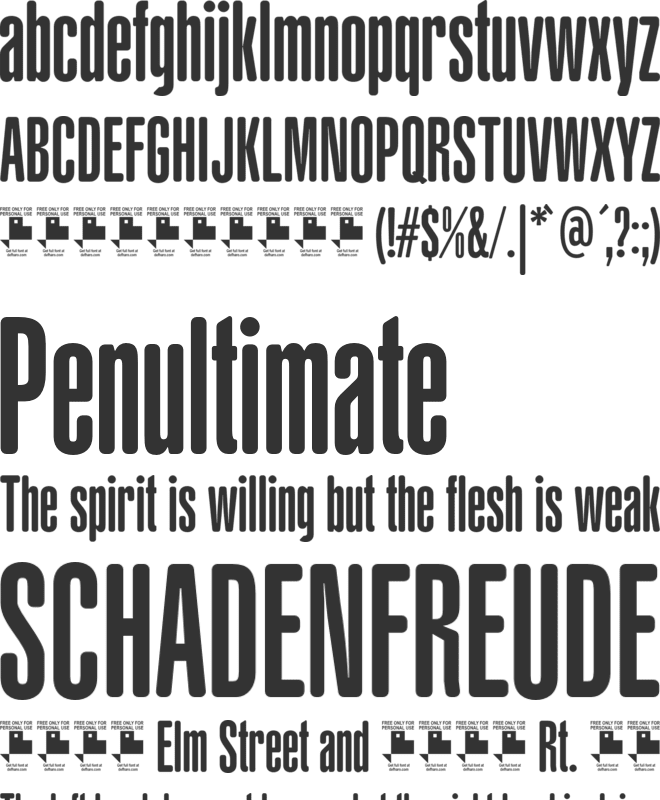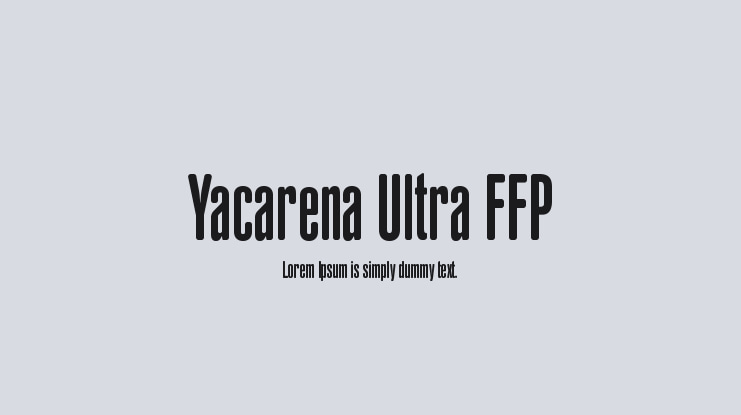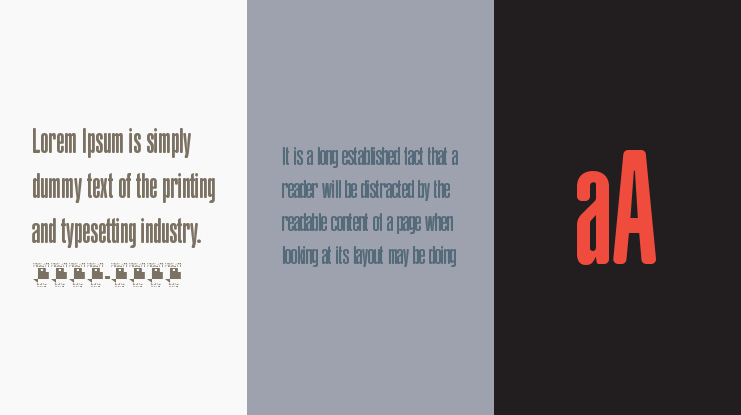
Yacarena Ultra FFP Font
Yacarena Ultra es un proyecto tipográfico surgido de mi necesidad redundante de disponer de una fuente muy condensada para ciertos trabajos de diseño gráfico donde la cantidad de texto en grandes títulos complican la composición. =========== Yacarena Ultra is a typographic project emerged from my redundant to have a very condensed font for some graphic design work where the amount of text in large titles need complicated composition. =========== Descarga gratis las versión completa desde mi web. Free download the full version in my website. Números disponibles en mi web Numbers available on my website Only for personal use. Sólo para uso personal. Licencia comercial disponible / Available commercial license.>> http://defharo.com/fonts/yacarena-ultra-sans-font/